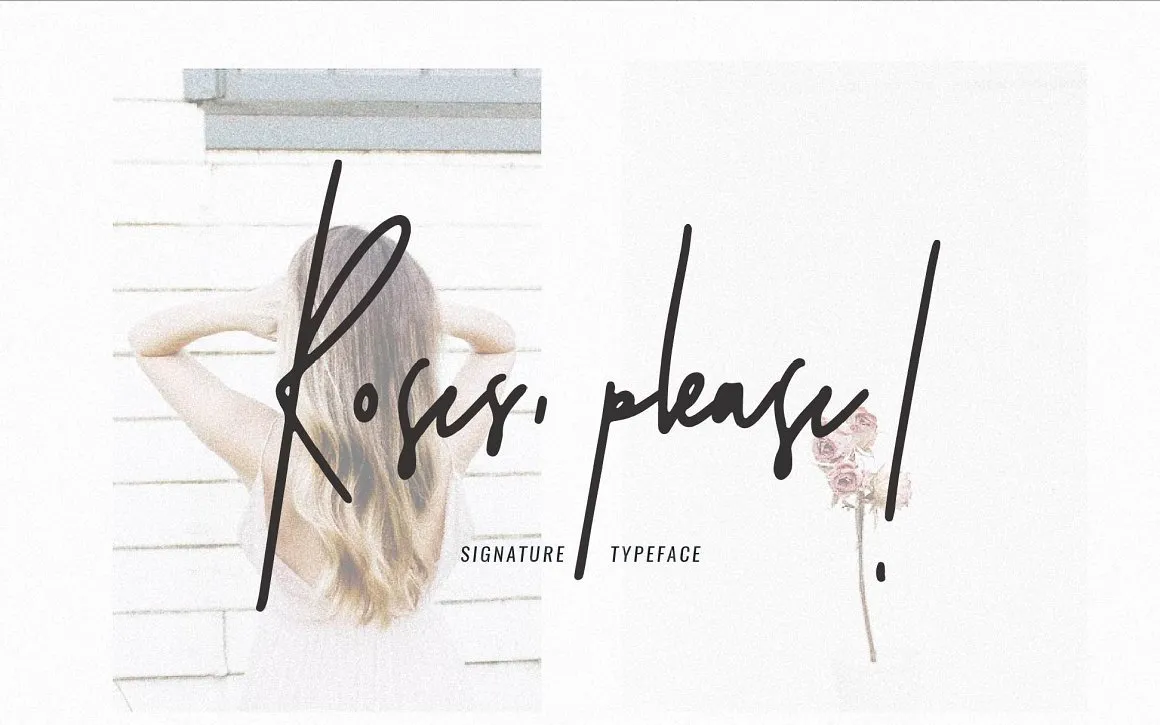
Roses, Please! Script Font – Download Grátis
Aqui está uma versão curta e envolvente para a descrição da página de download do ‘Roses, Please!’ Script Font: ‘Introduzimos “Roses, please!” Desenvolvida por Sinikka Li, esta é uma fonte premium disponível na CreativeMarket. Embora seja usualmente vendida, está gratuita hoje para download. “Roses, please!” é um tipo de assinatura escrita a mão que vem em duas versões diferentes. Suas linhas livres e descontraídas o tornam perfeito para logotipos femininos, citações impressas, cartões de convite de casamento, cabeçalhos de mídia social, embalagens de produto e muito mais.’